Gaya font yang elegan biasanya memiliki huruf tipis, garis dan bersih, variasi jenis fontnya cukup beragam. Ketika menciptakan desain pada canva dan ingin menciptakan desain elegan gunakan font elegan yang menarik. Font script elegan pada Canva cocok untuk digunakan pada jenis desain elegan seperti logo, poster dan konten media sosial.
Berbicara soal font elegan ini biasanya memiliki ciri gaya huruf bersih, garis tipis, garis halus tanpa dekorasi dan efek visual. Untuk penggunaan font elegan seperti script dan serif yang tipis sering kali identik dengan logo brand kecantikan dan fashion. Untuk jenis desain lainnya ada banyak desain yang bisa menggunakan font elegan sesuai kebutuhan atau tema desain.
JENIS-JENIS FONT YANG ELEGAN
Font yang elegan meneng memiliki ciri umum font tipis dengan garis halus, namun variasi ini bisa ditemukan pada berbagai jenis font. Setiap gaya huruf yang tipis bisa tampil elegan namun menciptakan mood yang berbeda. Berikut beberapa jenis font elegan dan contoh penggunaan yang paling sering, yaitu:
Script Tipis
Font script yang memiliki gaya huruf seperti tulisan tangan ini terlihat alami dan memiliki garis-garis elegan. Biasanya jenis font script yang tipis akan tampil elegan sehingga cocok untuk digunakan pada tema desain elegan. Beberapa contoh penggunaan font script yang elegan ini pada desain logo kecantikan dan fashion.
Tak hanya itu desain elegan pada undangan pernikahan juga kerap menggunakan font script tipis, seringkali dikombinasikan dengan font serif. Banyak juga desain kemasan produk kecantikan menggunakan font script tipis untuk menciptakan kesan mewah dan premium.
Serif Modern Lancip
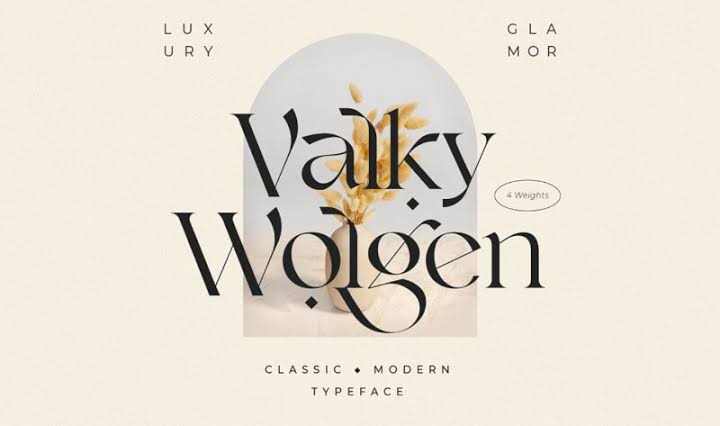
Font yang memiliki serif juga bisa tampil elegan jika memiliki gaya serif lancip dan tipis, gaya hurufnya juga harus tipis dan elegan. Tampilan serif modern yang bersih dan lancip seringkali cocok untuk menciptakan kesan elegan. Font serif modern banyak digunakan pada logo fashion karena membuat brand tampil high-end dan mewah.
Penggunaan font serif yang elegan juga kerap ditemui pada logo skincare dan kosmetik karena tampil feminim. Terkadang font serif digunakan pada jenis logo wordmark karena memudahkan keterbacaan nama brand serta mencerminkan identitas brand yang mewah. Meski populer untuk bisnis kecantikan dan fashion, font serif elegan juga bisa digunakan untuk brand coffee, logo cafe hingga brand perhiasan.
Sans serif Tipis dan Modern
Jenis font yang sederhana dan bersih ini juga bisa tampil elegan jika menggunakan gaya font tipis. Hindari menggunakan sans serif tebal untuk menciptakan kesan brand yang elegan. Gaya font sans serif modern dengan garis halus dan ujung lancip, biasanya akan cocok untuk digunakan pada logo yang profesional dan mewah.
Tak hanya serif, font sans serif juga banyak ditemui dalam desain logo brand kecantikan, fashion dan perusahaan. Gaya huruf yang elegan dan sederhana memudahkan untuk dibaca sehingga membangun identitas merek yang mudah diingat pula. Pada desain kemasan kosmetik dan skincare font elegan sans serif akan memudahkan informasi terbaca, namun masih sesuai dengan citra brand.
Display Melengkung
Font display juga banyak yang memiliki gaya huruf elegan, gaya font display tak hanya unik dan nyentrik. Beberapa gaya font display memiliki tampilan elegan dengan garis melengkung tipis seperti ornamen. Jenis font display serif atau script biasanya akan tampil elegan dengan gaya huruf tipis.
Penggunaan font display elegan akan cocok untuk kebutuhan desain poster film fantasi, desain sampul buku fantasi hingga desain kemasan yang unik. Gaya font display yang unik akan cocok mencerminkan kesan elegan dan magis dengan kombinasi dekorasi ornamen yang menarik.
FONT CANVA SCRIPT FREE UNTUK DESAIN
Ketika ingin menggunakan jenis font script untuk menciptakan desain yang elegan pada aplikasi desain seperti canva, pastikan memilih gaya font menarik. Beberapa font canva mungkin berbayar, jika ingin menggunakan versi gratis pilih gaya font script elegan yang gratis. Berikut beberapa font script yang free digunakan pada canva untuk desain elegan:
Slight
Jenis font script ini memiliki garis elegan dengan gaya huruf mirip, garis huruf yang halus menciptakan tampilan elegan. Font yang tampak mengalir halus tersebut akan cocok digunakan pada jenis desain elegan seperti desain undangan. Font tersebut bisa sulit terbaca pada ukuran kecil, sehingga bisa digunakan sebagai font judul pada desain undangan. Gaya font yang halus tersebut cocok juga untuk kemasan produk perhiasan yang mewah dan elegan.
La Luxes Script
Untuk font satu ini memiliki tampilan huruf lowercase yang lebih kecil dari huruf versi kapitalnya. Sehingga tampilan teks akan terlihat lebih menarik dan memiliki kontras visual yang menarik. Gaya huruf pada font ini tak hanya elegan tetapi terlihat alami seperti tulisan tangan. Font ini tampil elegan dan feminim sehingga akan lebih relevan untuk kebutuhan desain brand kecantikan.
Gaya huruf yang elegan akan tercipta dengan menggunakan garis tipis dan halus serta huruf yang bersih. Font yang elegan dengan huruf tipis biasanya termasuk jenis script, serif, sans serif dan beberapa gaya font display. Gaya font script tipis biasanya banyak digunakan untuk logo fashion, kecantikan, perhiasan hingga desain poster. Font script pada aplikasi canva tersebut free untuk digunakan dalam menciptakan gaya desain yang elegan dan mewah.